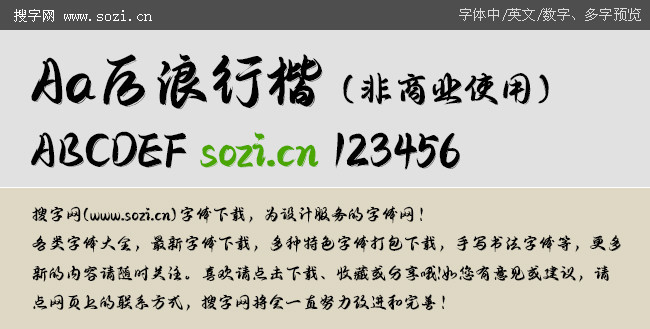
Aa后浪行楷
搜字網(wǎng)給大家提供一款A(yù)a后浪行楷(非商業(yè)使用)中文字體下載,該字體是一款手寫書法中文字體,該字體字型非常的流暢可愛,且自帶有陰影立體效果,具有很好的視覺感,適合書裝設(shè)計(jì)、包裝設(shè)計(jì)、海報(bào)設(shè)計(jì)等應(yīng)用(此字體為個(gè)人非商用版,商用可以聯(lián)系QQ:1006760504)。